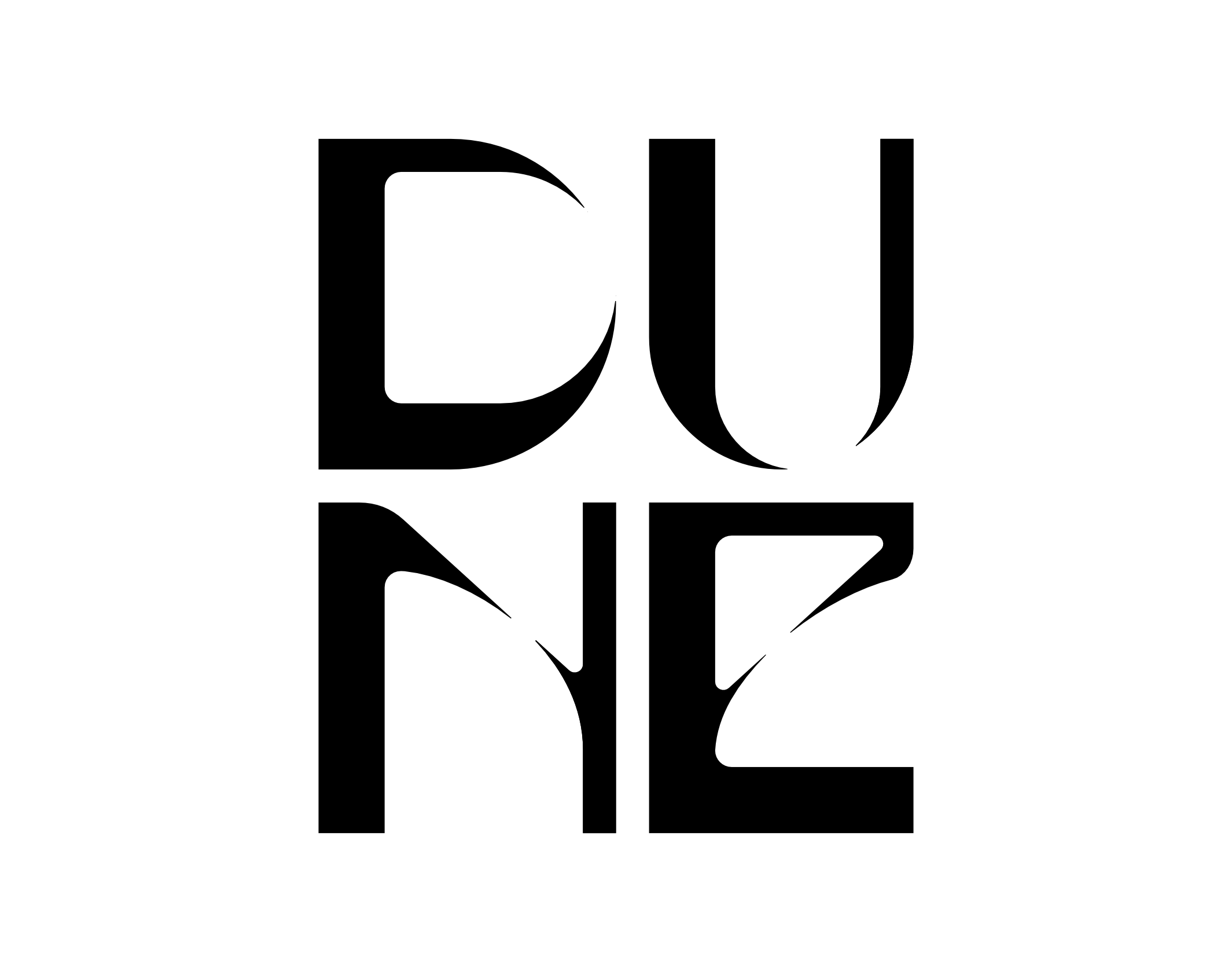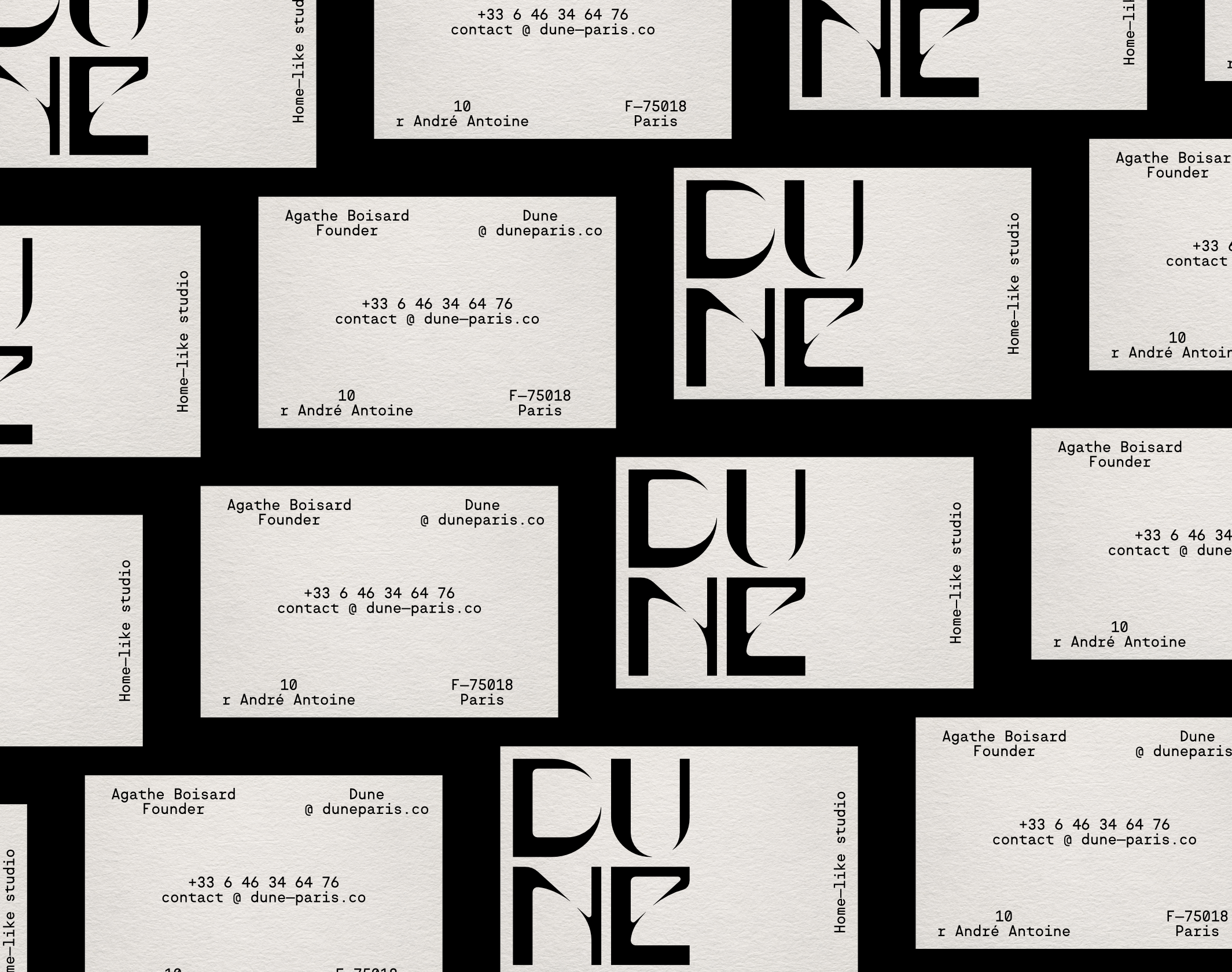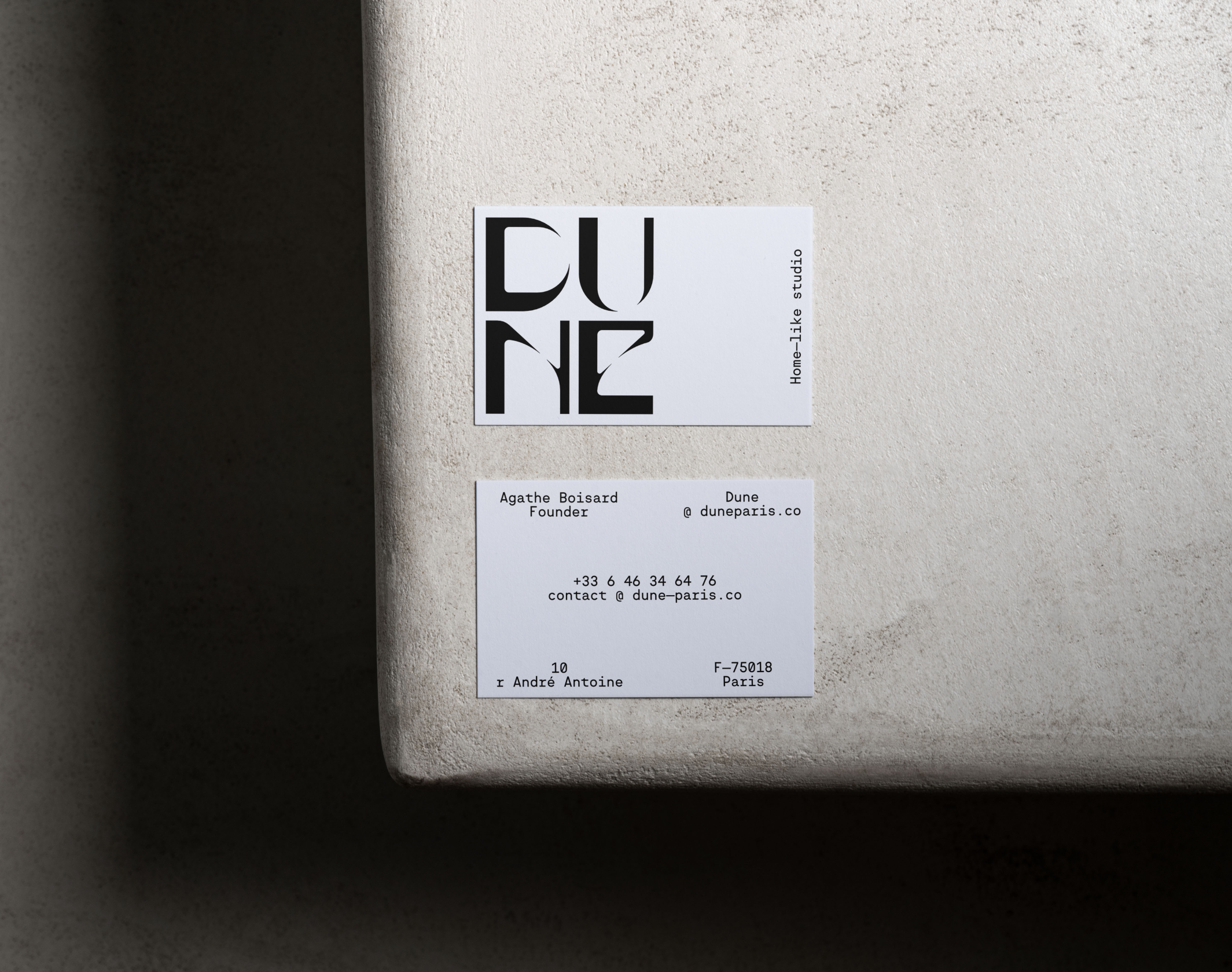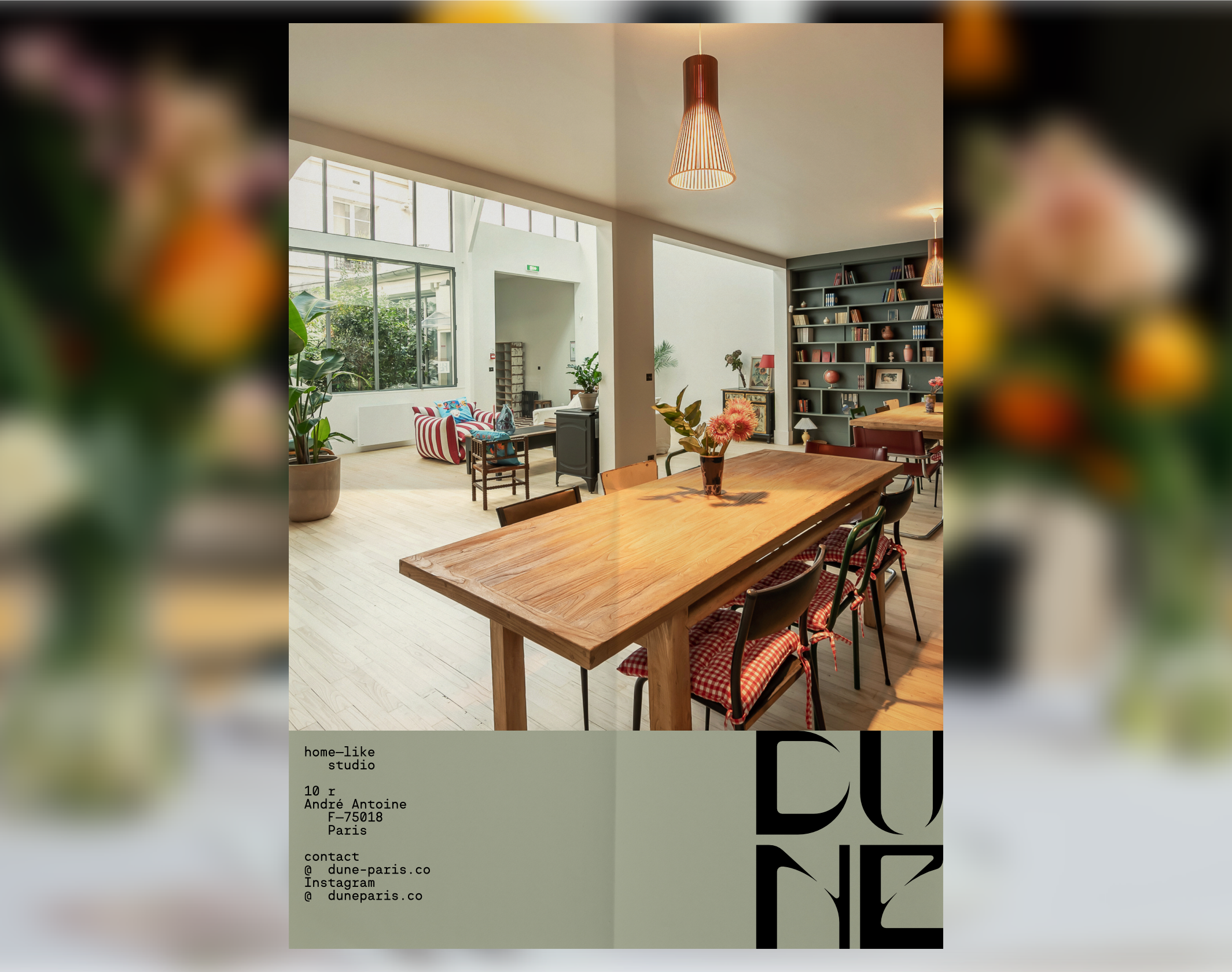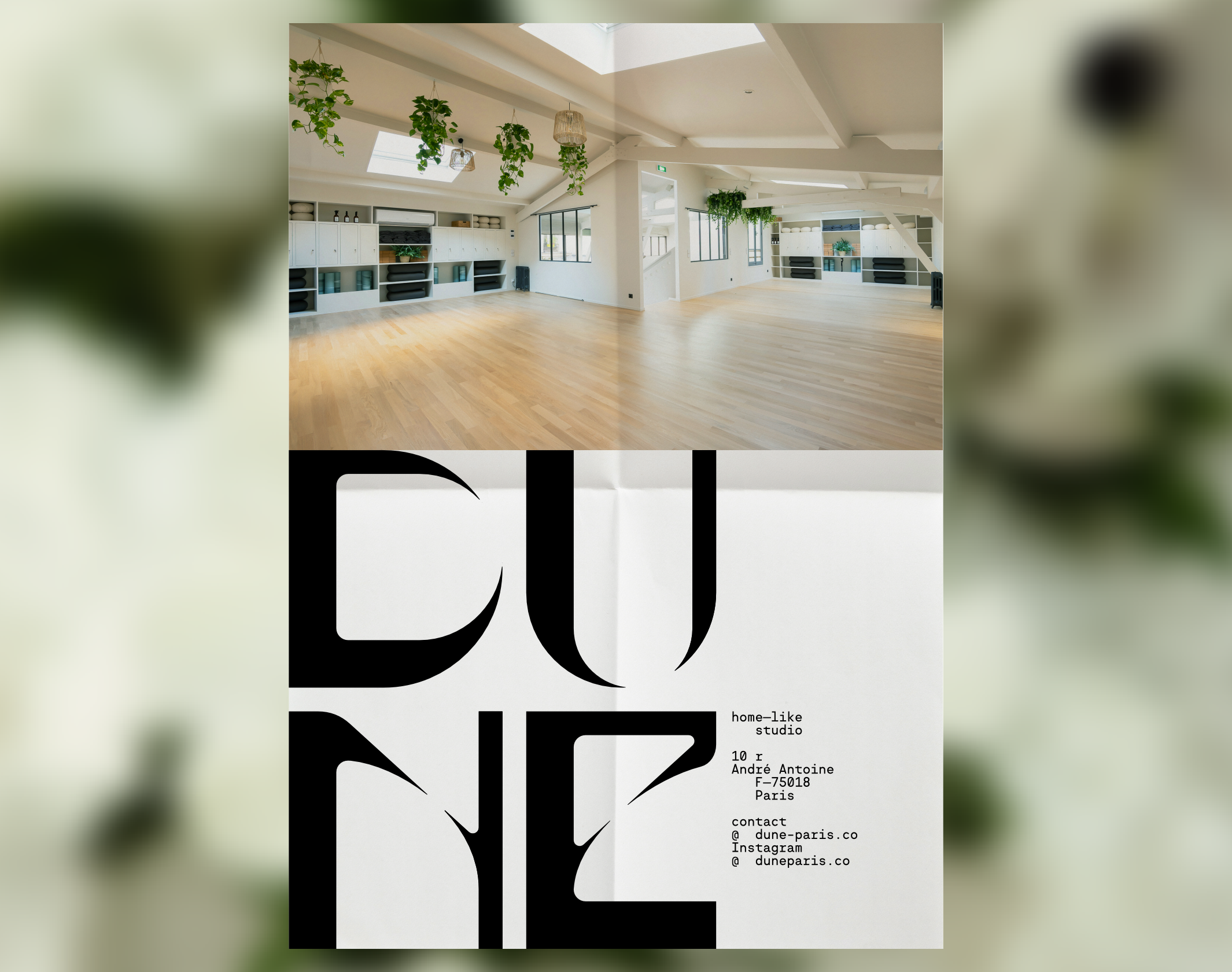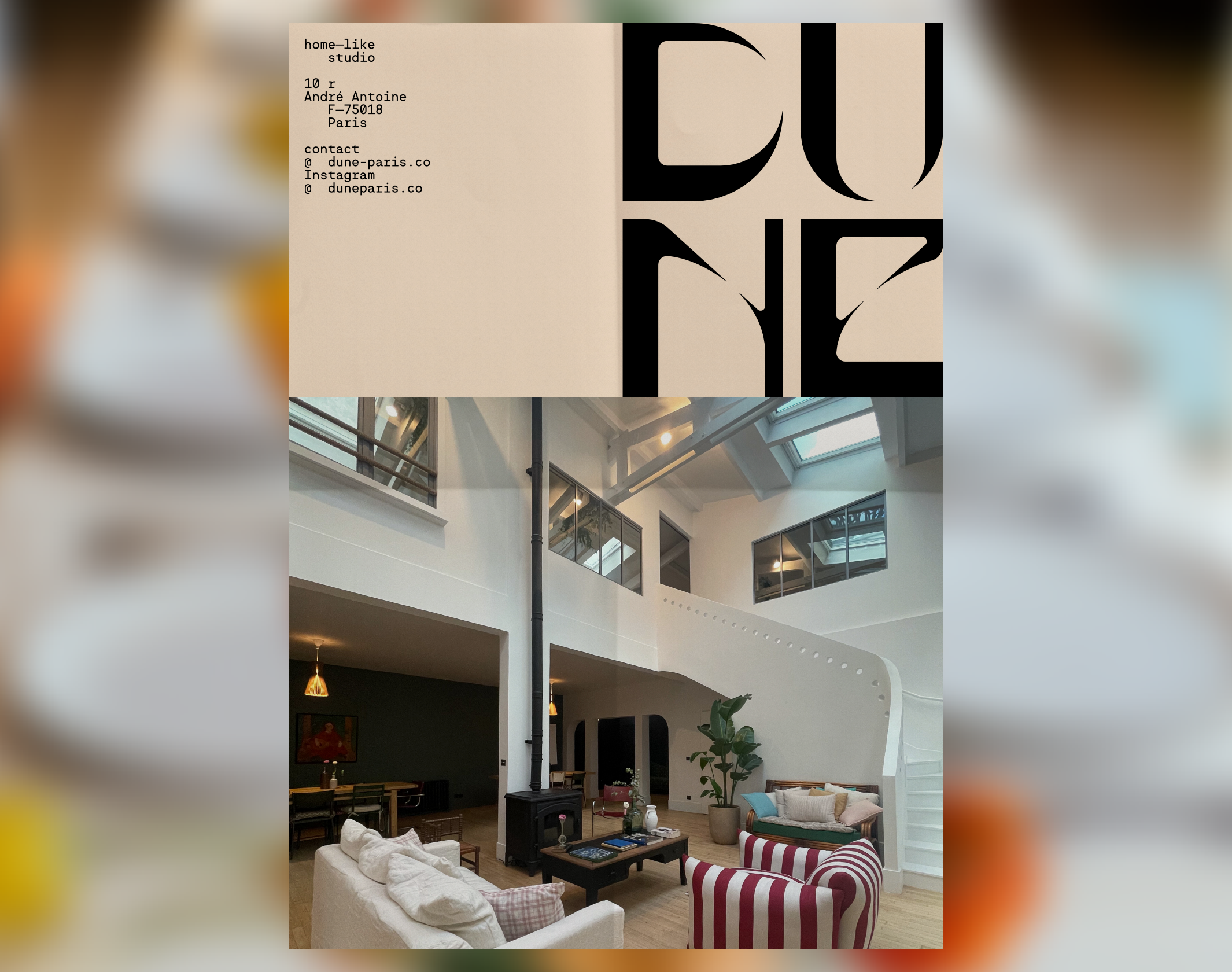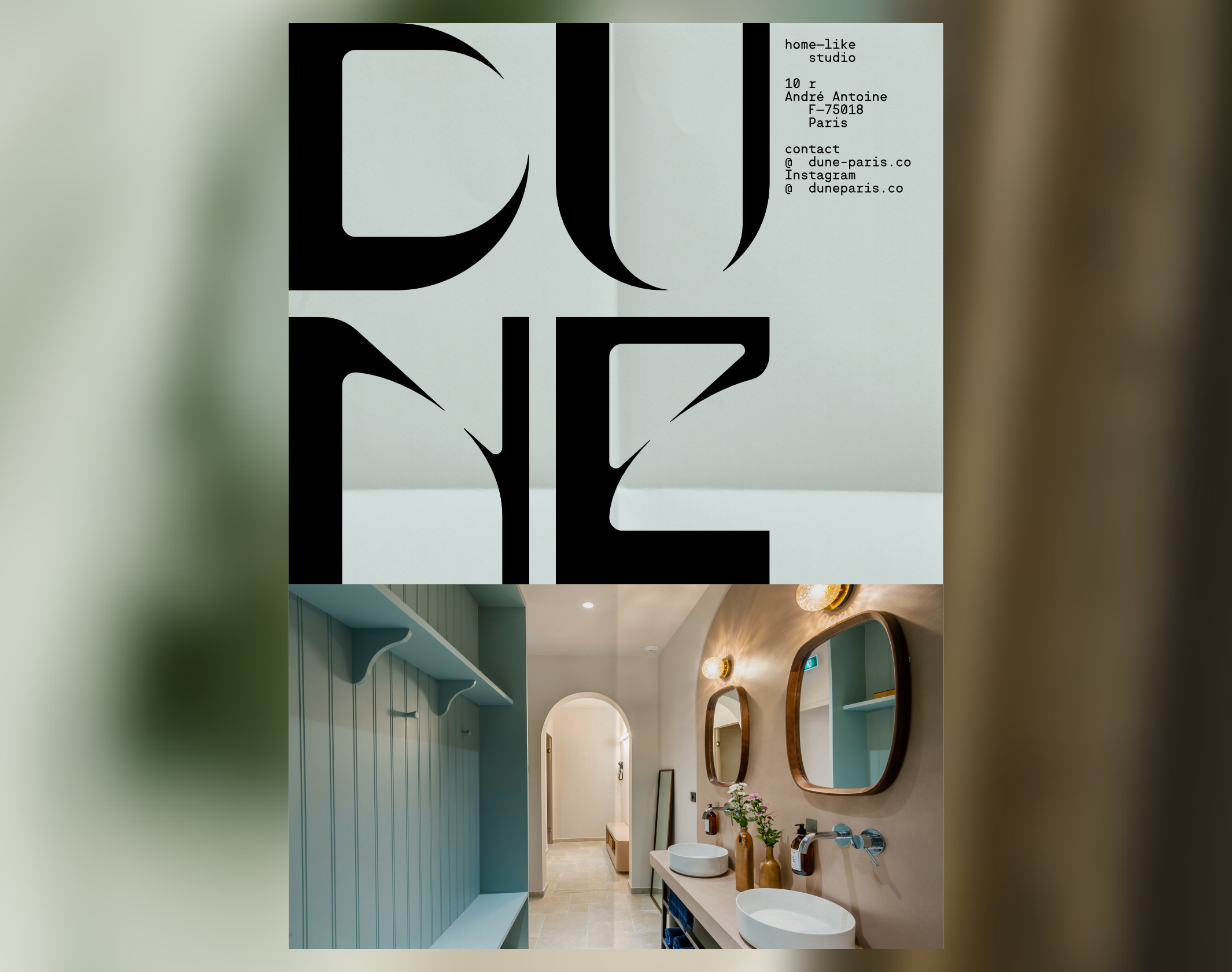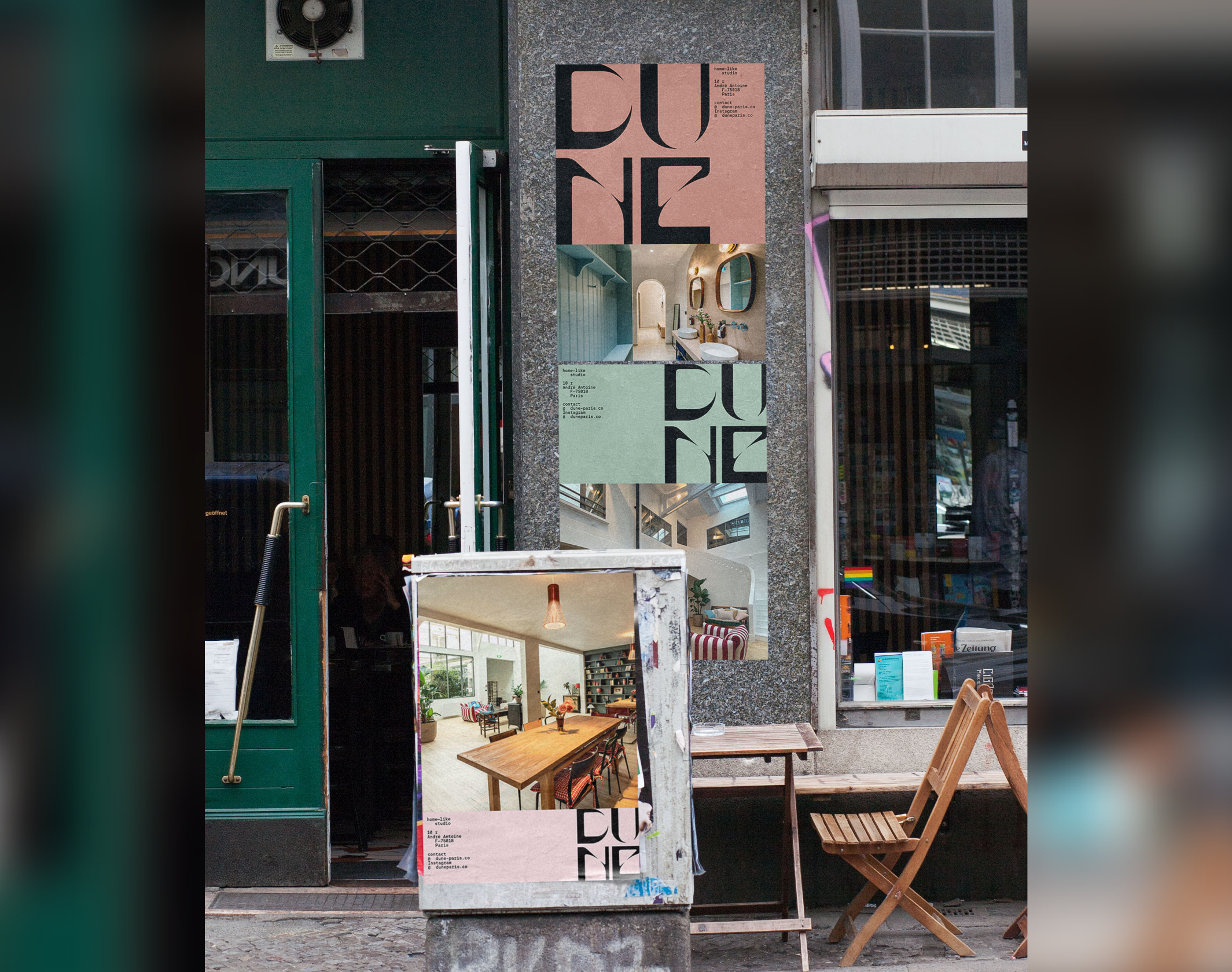
Dune
Dune, loft créatif à Montmartre, fusionne art et bien-être avec une identité visuelle inspirée du yoga, conçue par Brand Brothers.
Ancien atelier d’artistes de 200 m² reconverti en loft dédiés aux réceptions et évenements, au coeur de de Montmartre, Dune est un lieu pensé pour stimuler la créativité et le bien-être au sein d’un environnement calme et intimiste. Ouvert fin 2022, Dune accueille plusieurs événements par semaine, autour du yoga, du sport, de la culture, de la méditation, du bien-être ou de lancements produits.
La fondatrice du lieu a chargé Brand Brothers d’en concevoir l’identité visuelle. Notre intervention graphique se veut légère mais iconique, reposant sur un typogramme conçu pour la marque, structuré et organique. Les caractères s’étirent en leur centre, illustrant le mouvement et la torsion des corps ; une référence à la passion de la fondatrice pour le yoga. L’identité se décline sur un ensemble de supports imprimés et digitaux, notamment sur un site internet designé par le studio AB Projets et développé par nos soins.